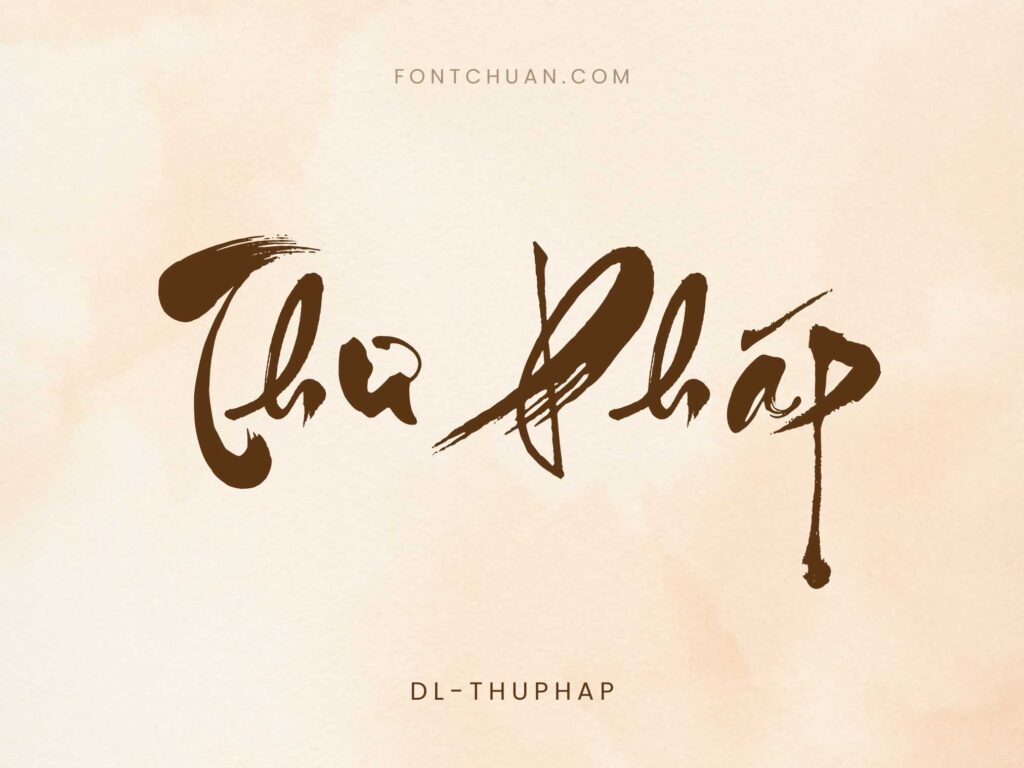
Font DL Thu Phap Việt Hóa
DL ThuPhap là một font chữ thư pháp mang đậm nét văn hóa Việt Nam, được thiết kế bởi Glorytype. Với những đường nét uyển chuyển và tinh tế, font này tái hiện vẻ đẹp của nghệ thuật viết chữ truyền thống, gợi nhớ đến hình ảnh ông đồ và những bức thư pháp xưa. Nhờ sự Việt hóa của Tduy, DL ThuPhap hỗ trợ đầy đủ các ký tự tiếng Việt, giúp người dùng dễ dàng ứng dụng trong các thiết kế mang đậm bản sắc dân tộc. Thành viên của Font Chuẩn đã sưu tầm và chia sẻ font này nhằm đáp ứng nhu cầu của cộng đồng thiết kế.
Về đặc điểm thiết kế, DL ThuPhap sở hữu các nét chữ mềm mại, linh hoạt, tạo cảm giác bay bổng và nghệ thuật. Font bao gồm đầy đủ chữ hoa, chữ thường, số và các ký tự đặc biệt, mang lại sự đa dạng trong việc sáng tạo. DL ThuPhap đặc biệt phù hợp cho các dự án thiết kế như thiệp mời, poster sự kiện, bao bì sản phẩm và các ấn phẩm quảng cáo liên quan đến các dịp lễ truyền thống như Tết Nguyên Đán, Trung Thu hay các sự kiện văn hóa. Trong lĩnh vực ngành nghề, font này được ứng dụng rộng rãi trong quảng cáo, thiết kế đồ họa, giáo dục và nghệ thuật, góp phần tôn vinh và bảo tồn những giá trị văn hóa truyền thống của Việt Nam.